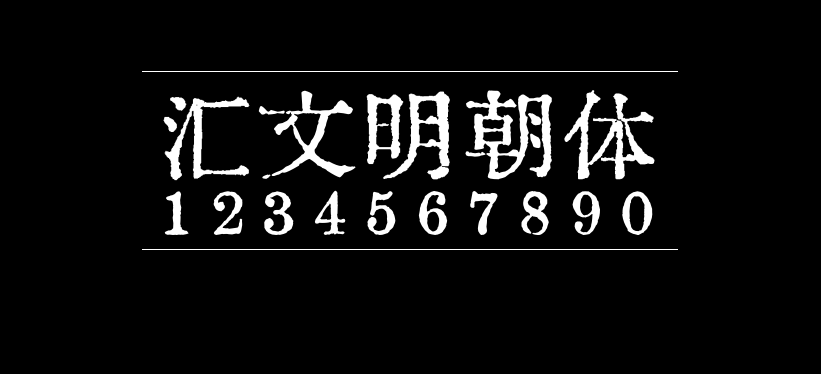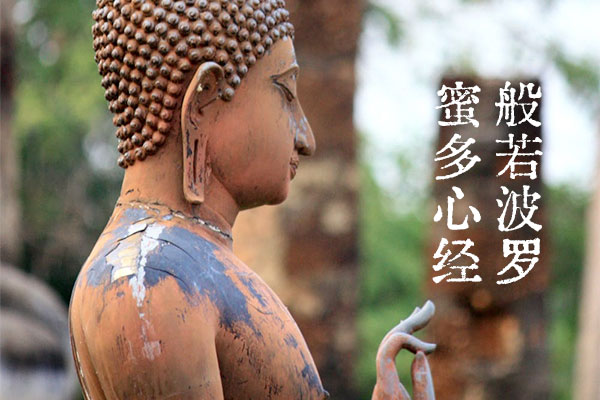
汇文明朝体
汇文明朝体是由百度旧字形吧网友天王帝廷发布的一款中文字体,汇文明朝体制作始于2019年1月份。因一切开始于是作者扫描《文汇报》上面的《汉字简化方案草案》。后来又收集、扫描了各种历史文献资料,汇总挑选而形成了这样一款字体。故名「汇文明朝体」。
汇文明朝体的字形来源主体为五六十年代官方各种汉字改革文件。简体字部分基本复原汉字简化后、字形改造前的书籍印刷体样貌。繁体字、传承字部分基本还原民国至共和国初期字形样貌。是比较原滋原味的旧铅字印刷风格。
汇文明朝体收录字符范围
全覆盖大陆「GB2312」标准6763字
全覆盖台湾「常用国字标准字体表」
全覆盖日本 常用、人名用、表外汉字表中的新字体
基本满足日常使用。
汇文明朝体平片假名及一些符號來源於Oradano明朝,其實要說起來,本字體的史祖就是Oradano明朝。因為最開始做的時候,我對於字體的字距、大小什麼的,完全不會調,也不知道要怎麼設置各種數據,所以就直接取了「Oradano明朝」這個字體作為殼子,把裡面的東西一一替換成我的字形,慢慢地替換到最後,才形成了匯文明朝體。就是説,其實這是一艘忒修斯之船。Oradano明朝的授權聲明如下